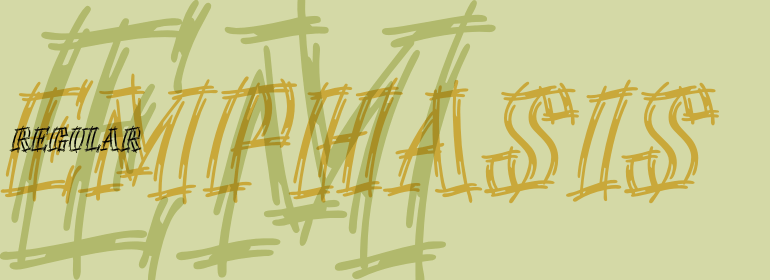
Emphasis™
Emphasis™,这款字体结构工整、笔画清晰,兼顾美观与易读性,适用于标题、正文、海报、包装、LOGO 等多种场景。字形优雅稳定,风格百搭耐看,适配日常排版与创意设计,让文字呈现更舒适、更具质感。Emphasis™一笔一画,皆是细节,以均衡的比例、流畅的线条打造舒适视觉体验,字形端正大气,风格简约现代。无论是商业设计、品牌宣传还是日常排版,都能轻松驾驭,让文字更有格调与力量。Emphasis™字体下载。
Emphasis是刻字艺术家Martin Wait的作品。其引人注目的双线效果突出了任何权威性的、现代风格的显示字体。Emphasis是一个全大写字母系统,它替代了传统的笔刷字体风格,无论用在何处都能提供休闲且稳健的外观。
Emphasis is the work of lettering artist Martin Wait. Its eye-catching double line effect highlights any display in an authoritative, contemporary style. Emphasis is an all caps alphabet which offers an alternative to conventional brush lettering styles, giving a casual yet robust look wherever it is used.